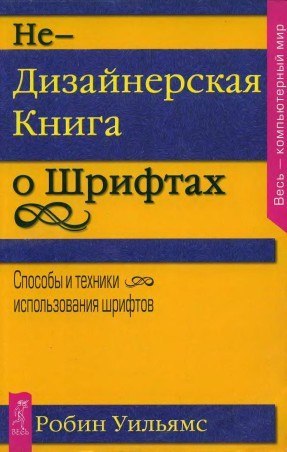
«Недизайнерская книга о шрифтах», Робин Вильямс
Главная цель автора любого текста — донести информацию до читателя. Выполнение этой задачи зависит не только от содержания сообщения, но и от того, как оно оформлено. Одним из главных элементов дизайна любого текста является шрифт.
С его помощью можно привлечь читателя, сделать процесс восприятия информации простым, не утомляющим, подчеркнуть важное в сообщении, отделить заголовки от текста и подписей под рисунками.
Эта книга о том, как использовать шрифт для этих целей.